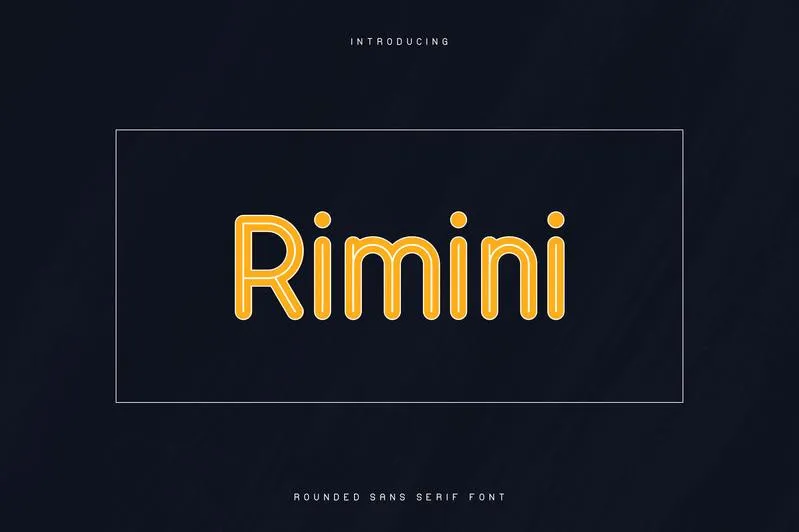
A Rimini Sans Serif é uma elegante tipografia sans serif que oferece sete fontes distintas, projetadas para atender a diversas necessidades digitais. Suas linhas são limpas e bold, proporcionando um formato agressivo e moderno que se destaca em ambientes tanto grandes quanto pequenos. Este conjunto de fontes é extremamente versátil, permitindo uma ampla gama de aplicações – seja para design gráfico ou web, ou até mesmo para uso empresarial e publicitário. Com suporte a várias línguas, a Rimini Sans Serif Font é ideal tanto para designers profissionais quanto para amantes da boa tipografia que buscam fontes modernas e potentes. Suas características simples e poderosas garantem uma experiência visual eficaz em qualquer formato de conteúdo digital ou impresso, tornando-a um recurso indispensável no arsenal de qualquer designer gráfico ou criador de conteúdo digital.